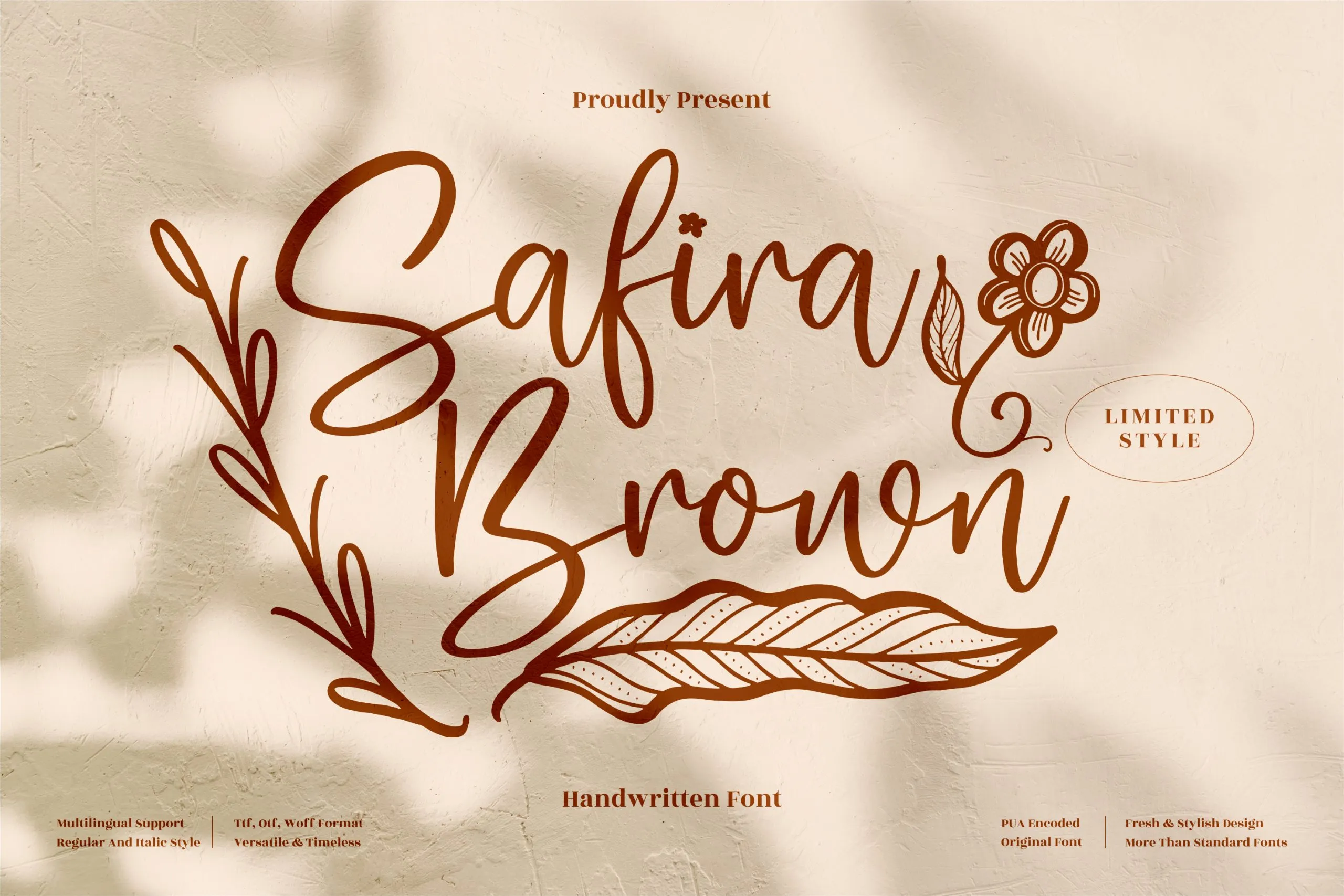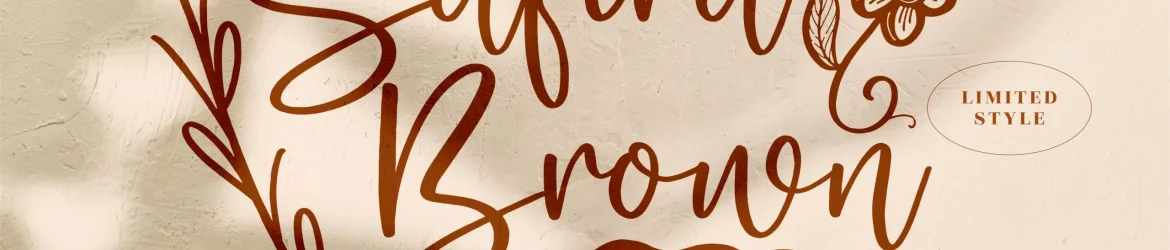
Safira Brown Font – Download Grátis
A Safira Brown é uma elegante fonte de escrita manual perfeitamente adaptada para uma ampla gama de projetos. Seja você designer de logotipos, criador de marcas de marca, ou responsável por criações de embalagens e produtos finos, a Safira Brown traz um toque autêntico que enriquece seu trabalho. Esta fonte é ideal para títulos ambiciosos em etiquetas de produto, para o design de carteirinhas, convites de aniversário ou cartões de cumprimentos, e até mesmo para capas de livros que transmitem um senso de sofisticação. A Safira Brown também se destaca como fonte ideal para criações de embalagens e pacotes personalizados, tanto nas etiquetas quanto no selo impresso. Além disso, a qualidade desta fonte garante uma presença única em camisetas, banners ou até mesmo na foto que você deseja destacar com um toque especial. Estamos certos de que essa fonte manuscrita irá fazer toda a diferença em sua próxima grande criação, proporcionando uma sensação de conforto e familiaridade. A Safira Brown é perfeita para quem busca incorporar um aspecto pessoal e autêntico aos seus projetos, oferecendo um toque único e sofisticado que o torna destaque no mercado.